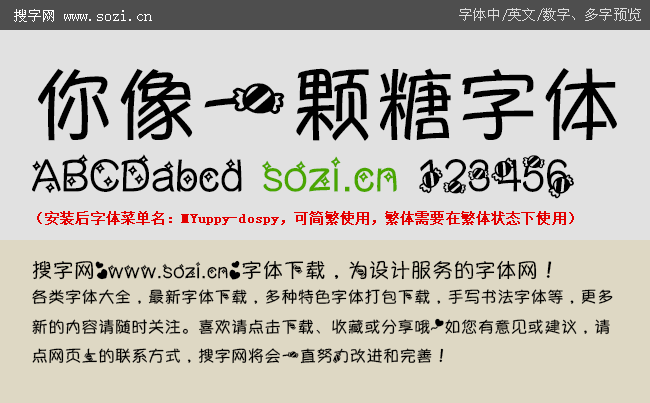
你像一顆糖字體
搜字網(wǎng)給大家提供一款很卡通的手機(jī)中文字體下載。修改者給這款字體叫你像一顆糖字體,這款手機(jī)中文字體以POP字體為原形,在筆畫間嵌入星星等卡通圖形,該中文字體趣味性強(qiáng),又保持了文字的識(shí)別度,非常適合喜歡卡通的朋友在手機(jī)上安裝使用。